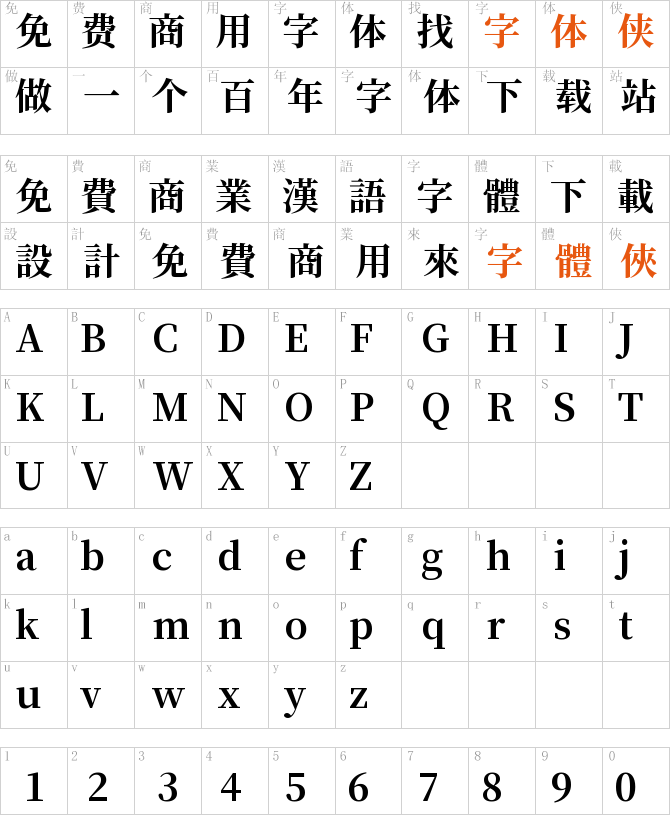
繁媛明朝字体缩略图:
繁媛明朝字体简介:
繁媛明朝:基于源样明体开发的简转繁字型 能处理一简对多繁。繁媛明朝是基于源样明体开发的简转繁字型,能处理“一简对多繁”。源样明体是基于思源宋体的开放原始码字型。
繁媛明朝字体版本更新:
Ver 1.006(2021/04/19)
- 添加报价转换
Ver 1.005(2020/11/23)
Ver 1.004(2020/10/04)
- 修复潜在的转换错误
Ver 1.003(2020/10/01)
Ver 1.002(2020/09/30)
- 修复v1.001中的转换bug(v1.001中不干你事被错误地转换为不干你事)
- 支持台语短语(如鼠标-> 滑鼠)
Ver 1.001(2020/09/30)
- 去除稀有汉字(为转换规则留出更多空间)
- 添加字母、数字、符号和标点符号
- 添加更多转换规则
- 支持 7 种字体粗细
Ver 1.000(2020/08/01)
- 繁媛明朝第一版正式发布